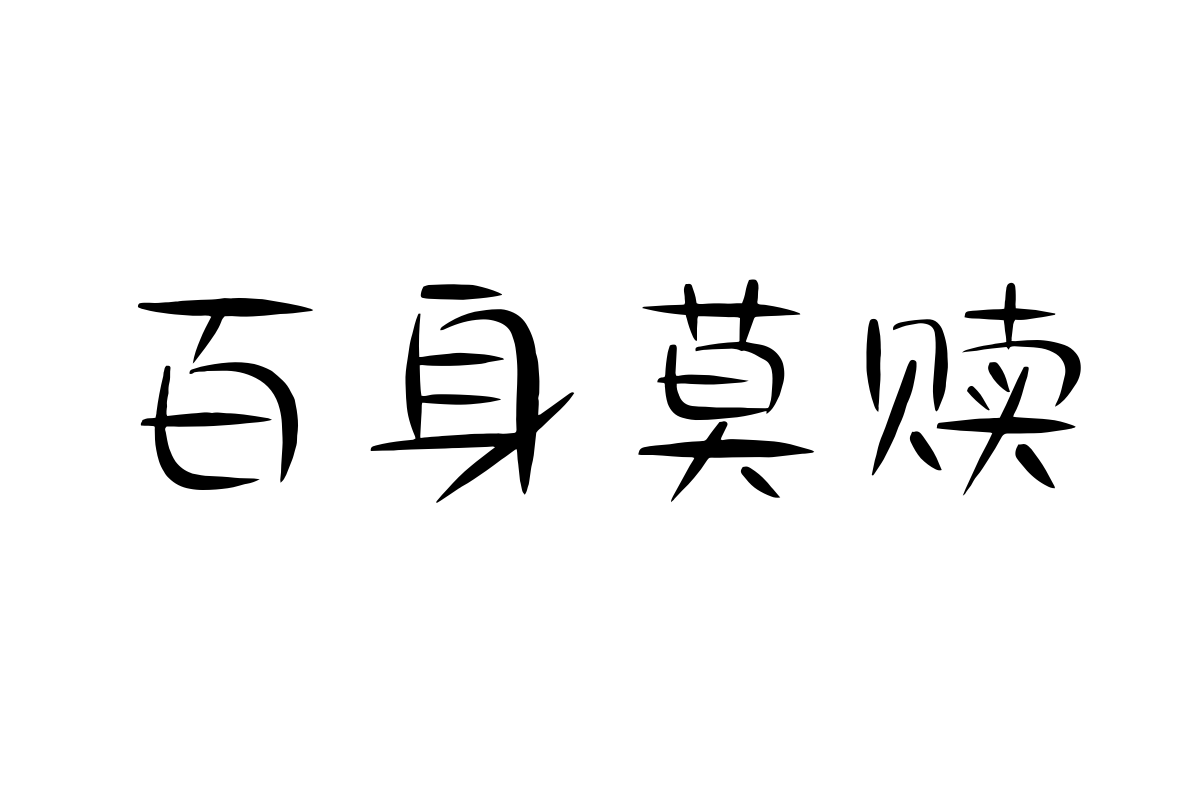
汉仪风波柳叶体简是一款由汉仪公司开发的字体,具有独特的风格和特点。这款字体采用了柳叶形的笔画,线条流畅自然,给人一种优雅的感觉。同时,字体的字形结构紧凑,笔画粗细适中,既适合用于标题、正文等需要强调的场合,也适合用于其他需要简洁明了的文本内容。此外,这款字体还具有一定的可读性和易识别性,适合在各种场景中使用。总的来说,汉仪风波柳叶体简是一款非常实用的字体,适用于多种应用场景。